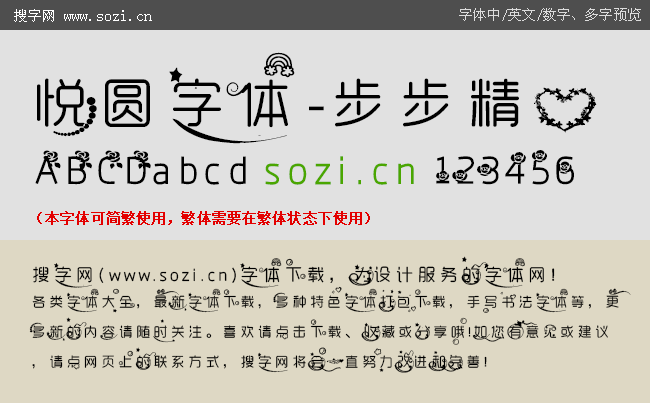
悅圓步步精心字體
搜字網(wǎng)給大家提供一款悅圓步步精心字體手機(jī)中文字體下載。這款手機(jī)字體是將悅圓體字體的一些筆畫換成了可愛(ài)的卡通圖案。造字工房悅圓常規(guī)字體為圓體字形,結(jié)構(gòu)秉承悅黑系列,筆畫風(fēng)格簡(jiǎn)潔,柔美優(yōu)雅。加入卡通圖案后趣味性實(shí)足,又保持了文字的識(shí)別度,特別適合喜歡手機(jī)字體個(gè)性一些的朋友在手機(jī)上安裝使用。